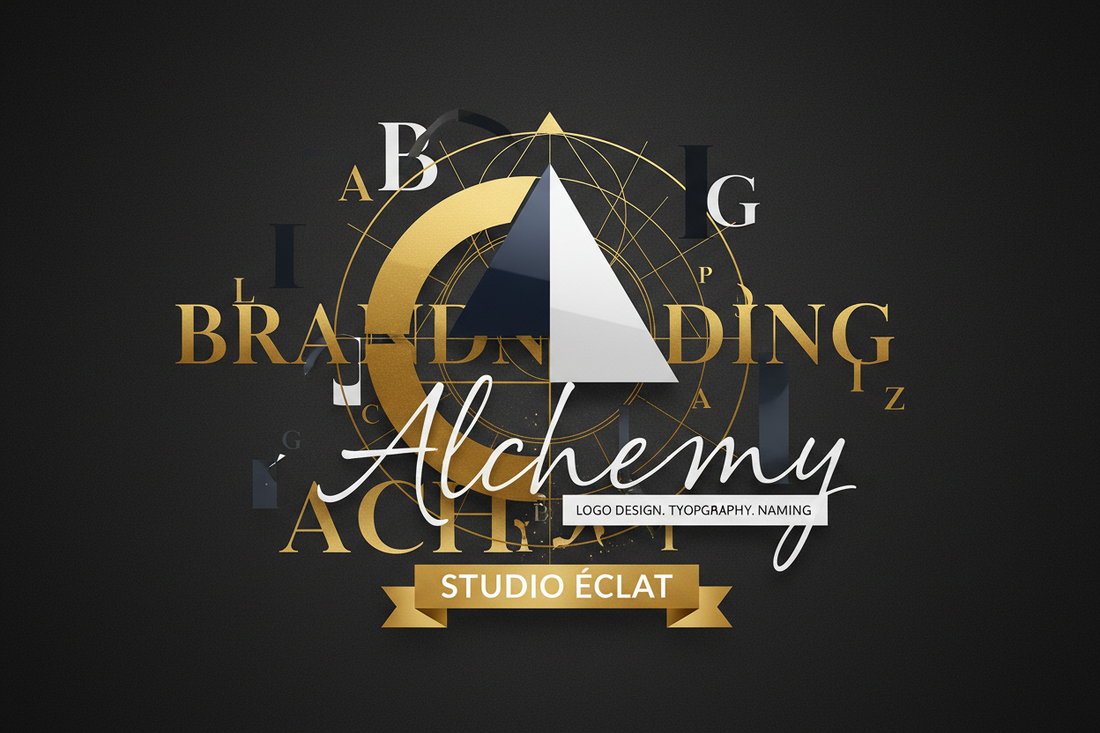
Logotipo, Naming y Tipografía: La Trinidad del Branding Profesional
¿Por qué el logotipo es el corazón de tu marca?
Tu logotipo es la primera impresión, el sello de identidad y el elemento más reconocible de tu marca. Pero un buen logotipo no nace de la nada: es el resultado de dos decisiones previas fundamentales — el naming (el nombre de tu marca) y la tipografía que lo representa. Cuando estos tres elementos se alinean, el resultado es una identidad visual que comunica, conecta y se recuerda.
El Naming: el primer ladrillo de tu identidad
El nombre de tu marca es la base sobre la que se construye todo lo demás. Un buen naming no es solo un nombre bonito — es una decisión estratégica que debe cumplir varios criterios:
- Memorable: Fácil de recordar después de escucharlo una sola vez.
- Pronunciable: En todos los mercados donde quieras operar.
- Único: Diferenciado de la competencia y disponible como dominio y en redes sociales.
- Significativo: Que evoque una emoción, un beneficio o un valor de marca.
- Escalable: Que no te limite si tu negocio crece o pivota.
Tipos de naming más usados en branding
- Descriptivo: Dice exactamente qué hace la marca. Fácil de entender, difícil de diferenciar. (Ej: General Motors)
- Evocador: Sugiere una emoción o experiencia sin describirla literalmente. El más poderoso para branding premium. (Ej: Apple, Amazon, Nike)
- Acrónimo: Iniciales de un nombre más largo. (Ej: IBM, BMW, H&M)
- Inventado: Palabras nuevas sin significado previo. Alta diferenciación. (Ej: Kodak, Xerox, Spotify)
- Fundador: El nombre del creador como marca. Construye autoridad personal. (Ej: Chanel, Ford, Armani)
La tipografía: cómo el nombre cobra vida visual
Una vez que tenés tu nombre, la tipografía decide cómo ese nombre se ve, se siente y se percibe. La misma palabra escrita en dos fuentes diferentes puede comunicar cosas completamente opuestas.
Imaginá la palabra LUXE escrita en:
- Una serif clásica como Didot → elegancia atemporal, alta costura
- Una sans-serif geométrica como Futura → modernidad, minimalismo, tecnología
- Una script manuscrita → calidez artesanal, personalidad creativa
El nombre no cambió. La percepción, sí. Eso es el poder de la tipografía en un logotipo.
¿Qué tipo de fuente usar en tu logotipo?
- Marcas de lujo y premium: Serif clásicas (Didot, Bodoni, Cormorant). Transmiten herencia y sofisticación.
- Marcas tech y startups: Sans-serif geométricas (Futura, Montserrat, Gilroy). Comunican innovación y claridad.
- Marcas creativas y artesanales: Script o display personalizadas. Aportan personalidad única.
- Marcas editoriales: Serif modernas (Playfair Display, Libre Baskerville). Autoridad y profundidad intelectual.
Los 4 tipos de logotipo y cómo el naming define cuál usar
1. Logotipo (solo tipografía)
El nombre escrito con una tipografía cuidadosamente elegida o personalizada. Funciona cuando el nombre es corto, fuerte y memorable. Ejemplos: Google, Coca-Cola, FedEx.
2. Isotipo (solo símbolo)
Un ícono sin texto. Requiere mucho reconocimiento previo. Ejemplos: la manzana de Apple, el swoosh de Nike.
3. Imagotipo (símbolo + texto separados)
El ícono y el nombre conviven pero pueden usarse por separado. El formato más versátil para marcas en crecimiento. Ejemplos: Adidas, Lacoste, Spotify.
4. Isologo (símbolo + texto integrados)
El ícono y el texto están fusionados y no pueden separarse. Ejemplos: Burger King, Starbucks.
El proceso: de naming a logotipo en 5 pasos
- Definí tu posicionamiento: ¿Qué emoción querés que evoque tu marca? ¿A quién le hablás?
- Elegí o validá tu naming: Verificá disponibilidad de dominio, redes sociales y marca registrada.
- Seleccioná 2-3 fuentes candidatas: Probá cómo se ve tu nombre en cada una.
- Definí el tipo de logotipo: ¿Solo tipografía? ¿Con símbolo? ¿Integrado o separado?
- Refiná y sistematizá: Ajustá el kerning, el peso y las proporciones. Creá versiones en positivo, negativo y escala de grises.
Errores frecuentes al diseñar un logotipo
- Usar demasiados elementos (símbolo + texto + slogan + colores = ruido visual)
- Elegir una fuente de moda que en 2 años se verá desactualizada
- No verificar cómo se ve el logo en tamaños pequeños (favicon, 16x16px)
- Ignorar la versión en blanco y negro
- No tener los archivos en vectores (SVG, AI, EPS)
Conclusión
Un logotipo poderoso no es suerte ni inspiración — es el resultado de un naming estratégico y una tipografía elegida con intención. Cuando estos tres elementos se alinean, tu marca habla antes de que digas una sola palabra.